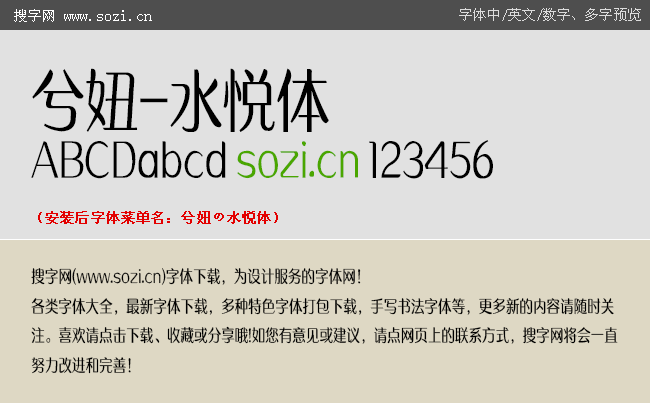
兮妞-水悅體
搜字網(wǎng)提供一款兮妞-水悅體中文字體下載,兮妞-水悅體是一款以宋體為原形進(jìn)行藝術(shù)設(shè)計(jì)的中文字體,適合應(yīng)用于廣告設(shè)計(jì)、名片設(shè)計(jì)、包裝印刷、產(chǎn)品設(shè)計(jì)等應(yīng)用。